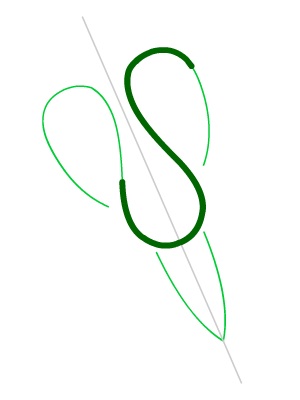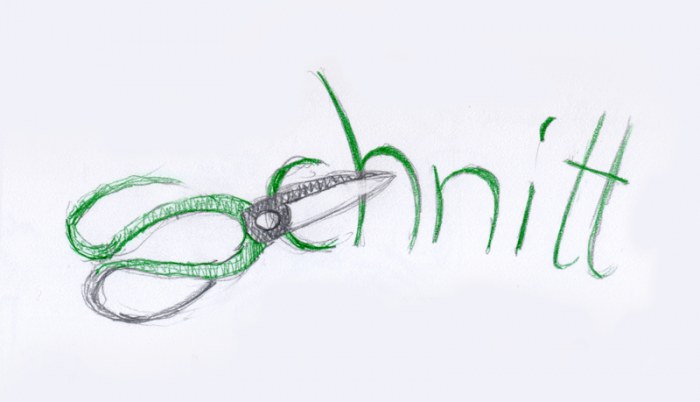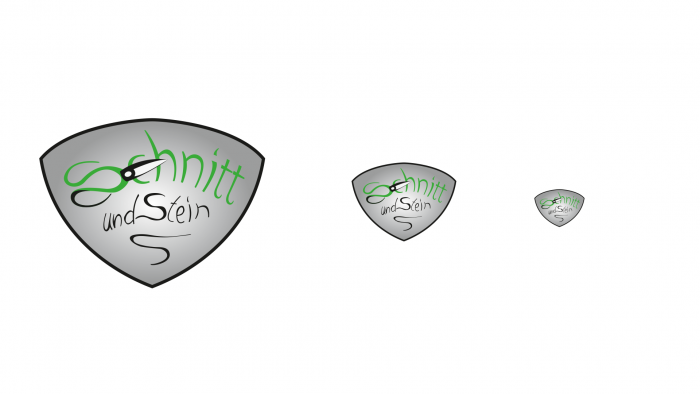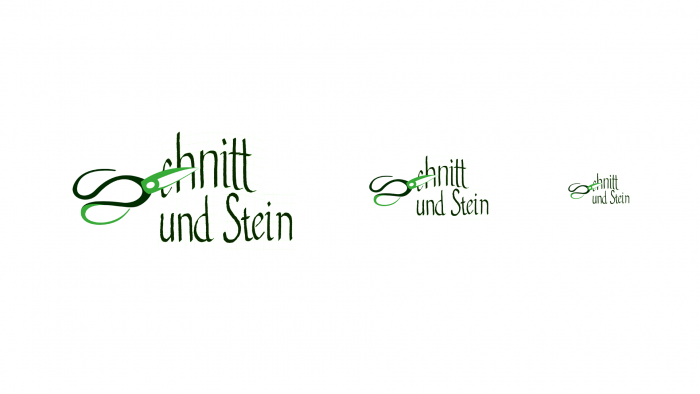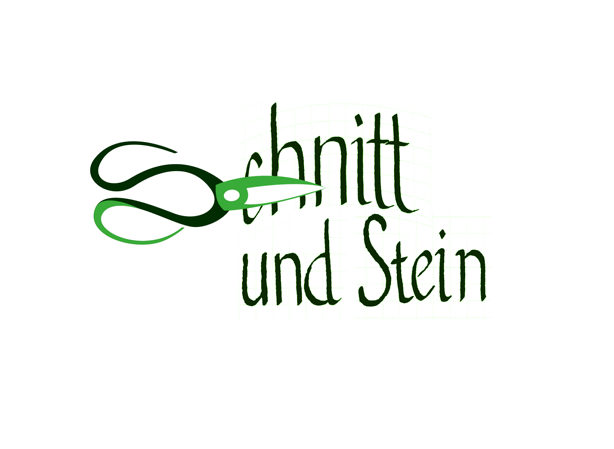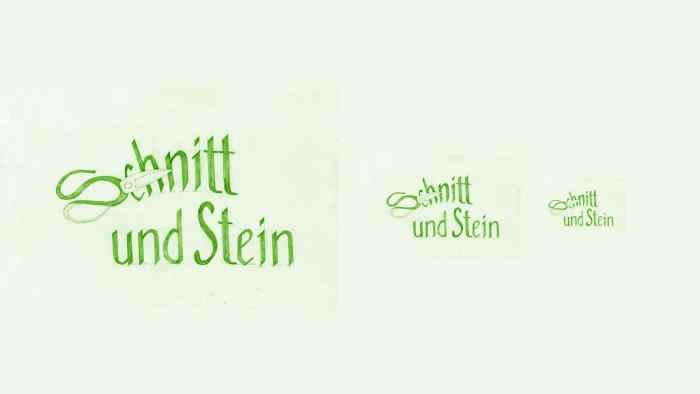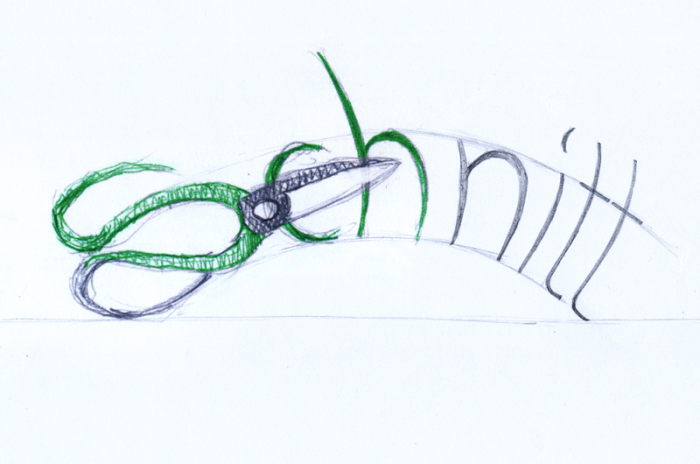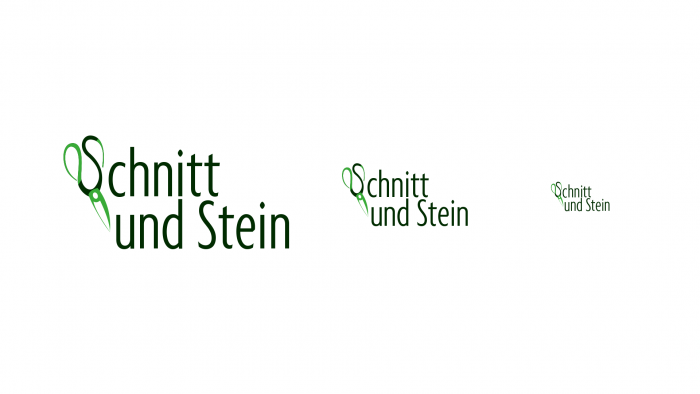
Hilfe bei Logoentwicklung
auf die Gefahr hin, dass ich wieder verschrien werde, Euch meine Arbeit machen zu lassen, hier ein erstes Scribble zu einem Logo dass ich für einen Bekannten machen möchte. Sein Gewerbe: Er ist Gartenbauer, seine Firma heißt Schnitt und Stein.
Hier die ersten beiden Skizzen:
Skizze #1: Als mir die Idee kam
Skizze #2: Etwas an den Buchstaben gearbeitet
Ich weiß, ich bin nicht so gut mit Schriften, habe mich etwas an der "Helvetica Neue" orientiert was "nitt" angeht, ansonsten wollte ich dass die Schrift eben etwas von Gras hat, daher der Schwung.
Kritik & Kommentare Willkommen!
p.s.: Bei der Buchstabenkombination "h n" im zweiten Entwurf ist die Lücke zu groß glaube.
Sehr schöne Idee!
Ich würde an Deiner Stelle da jetzt den Text „und Stein“ noch etwas kleiner darunter skizzieren und wenn Du mit dem Gesamtaufbau zufrieden bist, dann würde ich für die Umsetzung keine Satzschrift verwenden sondern das Ganze von Grund auf selber bauen.
Wenn Du da jetzt mit Satzschriften drangingest (speziell mit so etwas nüchternem wie der Helvetica!), dann verlöre Dein Entwurf ganz schnell seinen Charme – und das musst Du unbedingt verhindern!
Schöne Idee, aber meine erste Intention war Schneiderschere, nicht Gartenschere, daher hatte ich spontan eine Änderungsschneiderei vor Augen.
Wobei es wohl auch japanische Gartenscheren deiner Bauart gibt …
Ich finde es unglücklich, daß die Form nur funktioniert, wenn man die untere Schleife der Schere farblich absetzt. Eine einfarbige Version des Logos kann es da nicht geben, die wäre aber für ein funktionieren unter verschiedenen Bedingungen unabdingbar. So scheint mir das eher eine Illustration zu werden als ein Logo.
Wenn man die untere Form mittels einer Outline darstellt, die obere Form aber vollflächig schwarz, dann lässt sich dieses Logo auch in Schwarzweiß darstellen.
nach einigem Herumspielen mit dem Entwurf und Funkstille bei meinem Bekannten für den das Logo ist, nun ein zweiter Entwurf.
Ich weiß, die Schrift wirkt unbeholfen, aber ich bin nicht so der Kalligraph (wie einige von Euch). Zur Not könnte ich einen Freund damit beauftragen mir die Schrift zu optimieren, aber einige Tipps von Euch, die in diese Richtung gehen würden mir erst einmal mehr helfen.
Kritik & Kommentare Willkommen.
also ich verstehe ehrlich gesagt nicht, warum du diese Wappen-/Polizeimarken-Form gewählt hast. Das würde ich einfach komplett weg lassen. Den Schnörkel unten drunter würde ich auch ersatzlos streichen. Stichwort: „Reduktion“.
Die Buchstaben von „und Stein“ tanzen irgendwie rum … warum haben diese keine gemeinsame Grundlinie und Richtung so wie „Schnitt“? Ich würde für beide Zeilen eine (optisch) gleiche Rundung wählen, diese insgesamt aber vielleicht etwas weniger als in deinem Entwurf. Außerdem vielleicht nicht symmetrisch, das würde etwas mehr Dynamik geben.
Zu deinen Buchstaben: Die Strichstärken(Kontraste) wirken unnatürlich und inkonsequent innerhalb der verschiedenen Buchstaben. Zum Beispiel ist das S in der zweiten Zeile relativ fett, das t dagegen deutlich zu maker, bei un entsteht ein Fleck/Knubbel. Diese sollten sich besser an denen eine klassischen Feder orientieren und vereinheitlicht werden.
Die Formen der Buchstaben sind auch nicht so optimal ;-) insbesondere das letzte n sieht seltsam aus.
Außerdem siehst du schon in deinem Posting, dass der Entwurf in kleinen Größen nicht funktioniert. Hier müsste eine Alternative her (wenn diese kleinen Größen gebraucht werden).
Ich finde die Idee ganz nett, wenngleich sie sehr naheliegend ist. Spätestens an dem Punkt solltest du aber merken, dass es schwer wird, diese äthetisch in eine Logoform zu bringen. Die Form der Scherenhebel harmoniert nicht mit den Buchstaben, das c wird sehr stark verdeckt, das Grün steht äußerst schlecht auf dem Grau usw.
Vielleicht geht man noch einmal zurück an den Anfang und versucht es mit einem anderen Ansatz.
@TobiW
Danke für die Verbesserungen. Ich werde Deinen Rat beherzigen und mit der Feder arbeiten
und versuchen das S, welches ja durch seine Funktion als Scherengriff unveränderbar ist,
mit den anderen Buchstaben (chnitt und Stein) nachzuempfinden.
Auch die Wappenform und den Schnörkel lasse ich wohl vielleicht eher weg, auch wenn mein Bekannter das gut fand!!
@StefanB
Ja, das c wirkt echt verdeckt und macht das Lesen schwer. Ich werde aber erst noch ein bisschen mit dieser Idee experimentieren -- ich habe ja Zeit, der Bekannte ist geduldig!
Hallo Gregor, ich stimme meinem beiden Vorrednern zu – die Wappenform braucht es nicht, den Grauverlauf im Hintergrund auch nicht. Beide Elemente fügen Deinem ursprünglichen Entwurf nichts hinzu, was ihn verbessern würde, im Gegenteil. Was Du auch beachten solltest ist die Informationshierarchie. Die Teile, die Du jetzt schwarz gemacht hast, wirken dominanter als die grünen Teile, was der Leserlichkeit und der schnellen Erfassbarkeit des Logos nicht dienlich ist. Versuche stattdessen doch mal, mit einem helleren Apfelgrün und einem etwas dunkleren Tannengrün zu arbeiten, kein Schwarz. Den Wortbestandteil »und Stein« würde ich mittig und gerade geschrieben unter das geschwungene »Schnitt« setzen und den Schnörkel untendrunter weglassen, den braucht das Logo auch nicht – Deine Ursprungsidee ist stark genug, um richtig umgesetzt ohne Stützräder zu funktionieren.  :-)
Zwar hier jetzt OffTopic aber ich kann nicht anders: